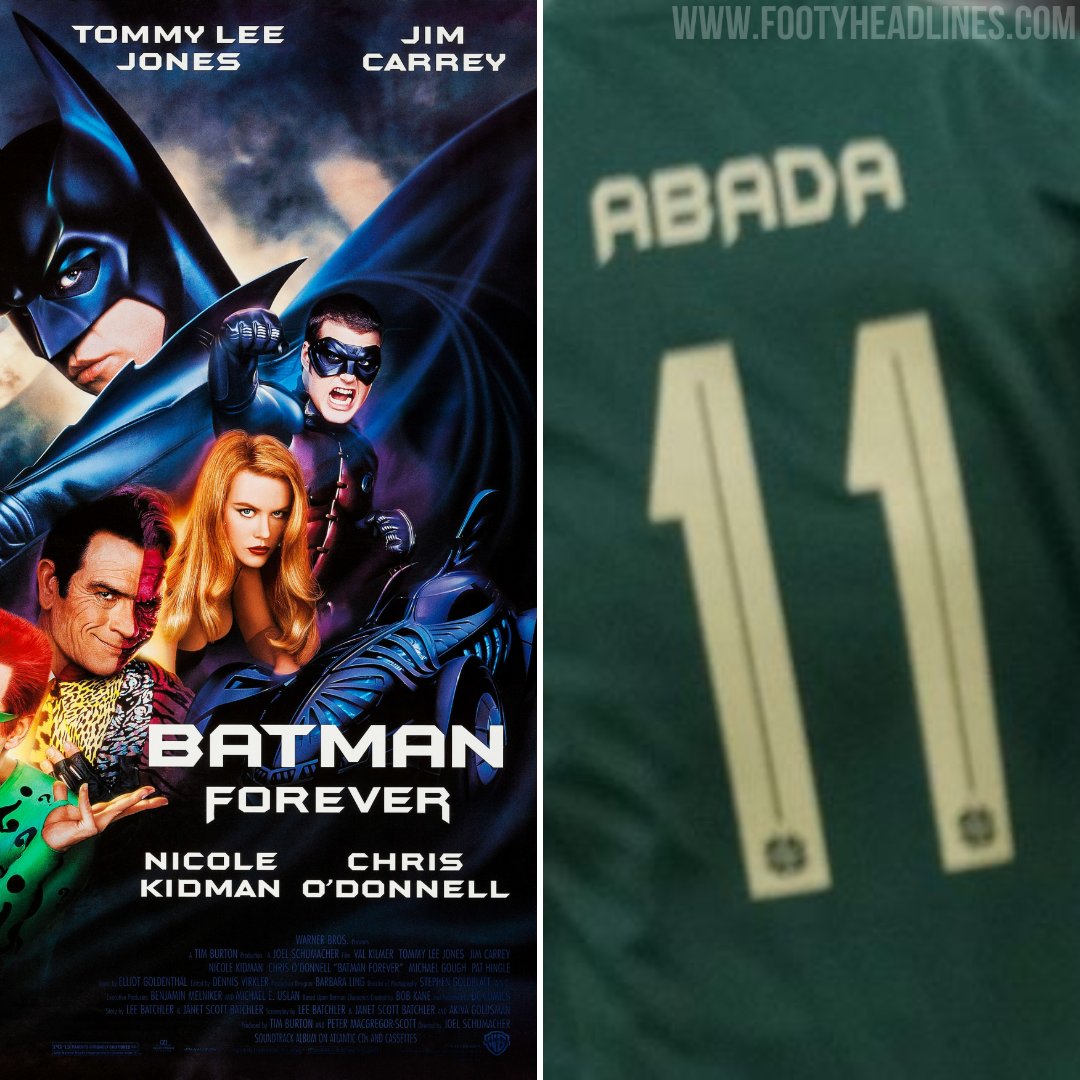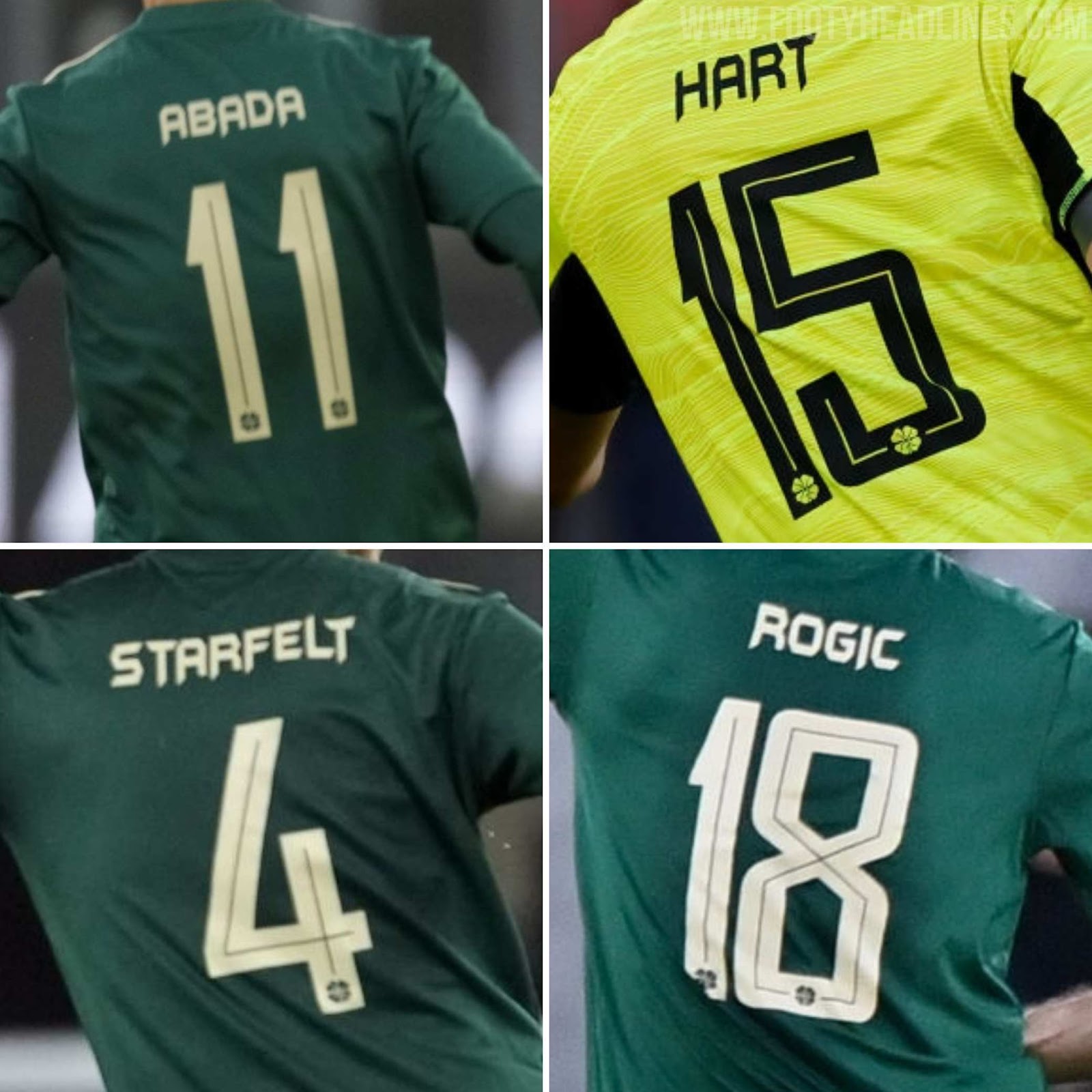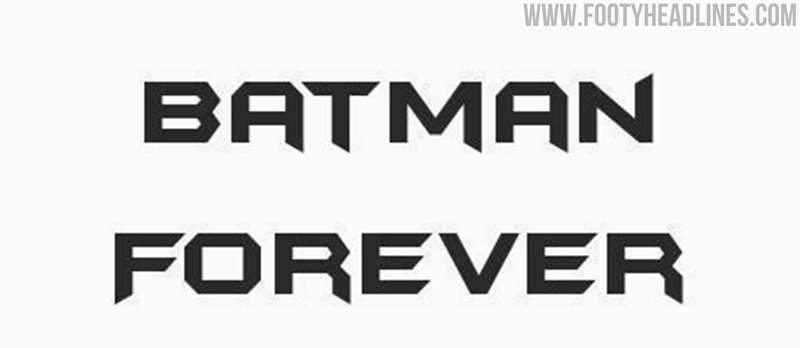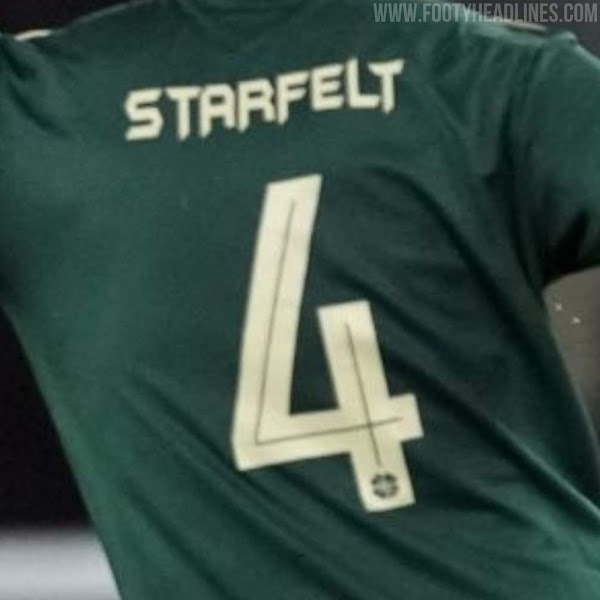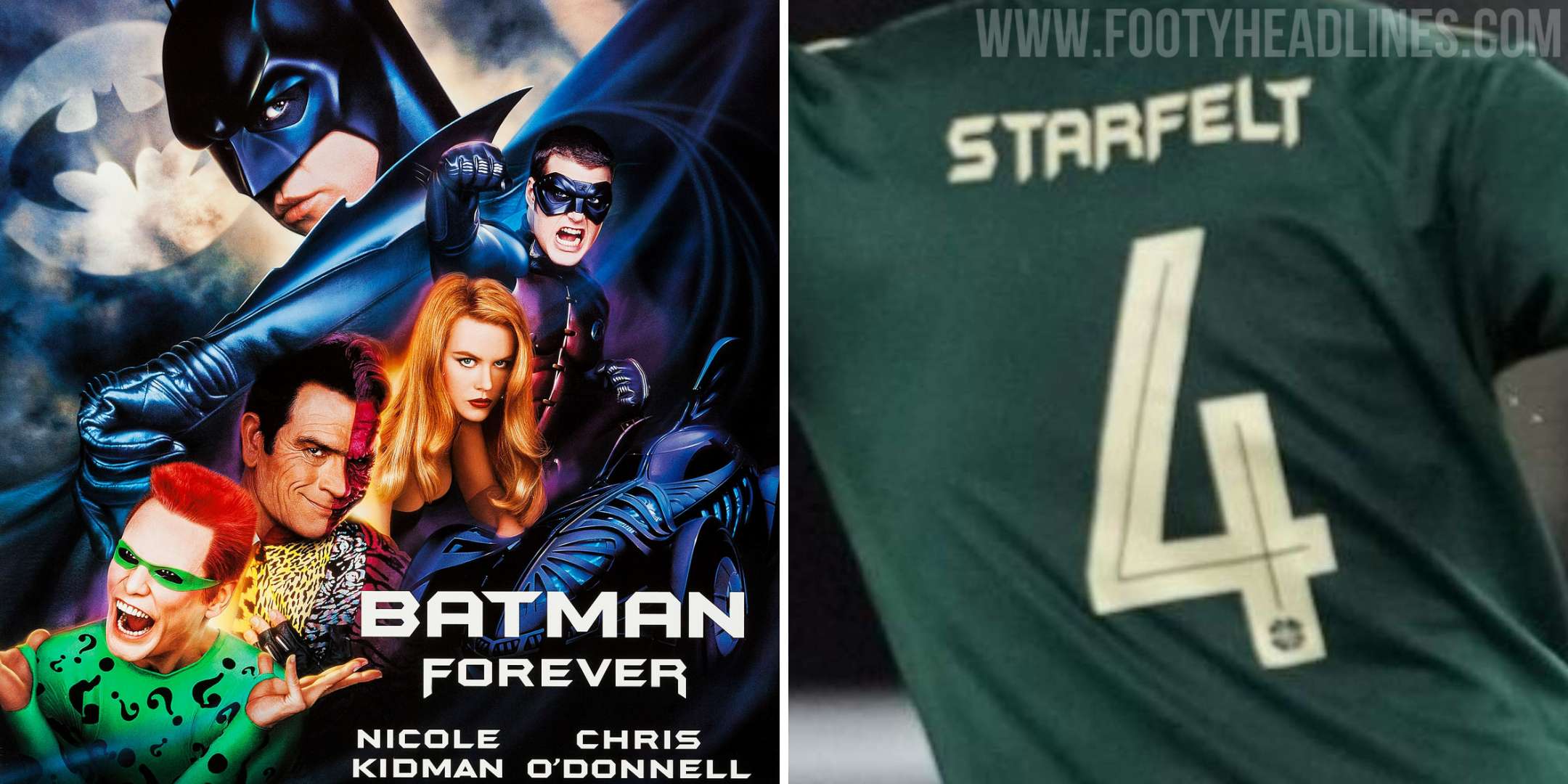
Celtic 21-22 International Trikot Font Revealed - Inspiriert von Batman Forever
Celtic wird die Schriftart nur in der Europa League tragen
Celtic wird die Schriftart in der Europa League 2021-22 (und möglicherweise in der UEFA Europa Conference) tragen, während sie in der schottischen Premier League und im Pokal die ligaweite Schriftart verwenden.
Celtic FC 21-22 Trikot Schriftzug
Die Celtic 21-22 Trikotschrift hat einen ganz besonderen Look und ist stark von Batman inspiriert. Die Buchstaben sind von der Schriftart inspiriert, die für Batman Forever verwendet wurde, während die Zahlen den Stil der Agency FB Schriftart haben.
Batman Forever ist ein amerikanischer Superheldenfilm aus dem Jahr 1995 unter der Regie von Joel Schumacher und produziert von Tim Burton, basierend auf der DC Comics Figur Batman.